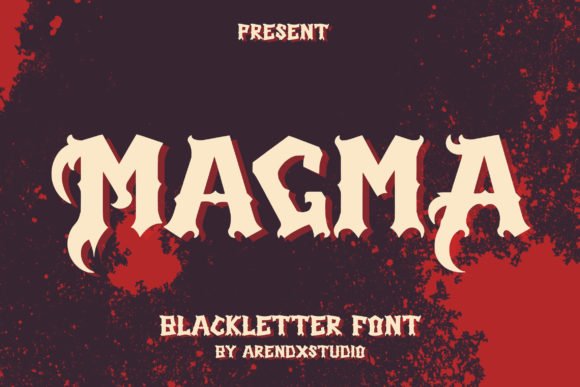
Creativefabrica Magma Font 2021
[Creativefabrica] Magma Font (2021)
Magma - это смелый, жуткий и драматичный шрифт с черными буквами.
Он может быть использован в различных дизайнах, требующих жуткого штриха.